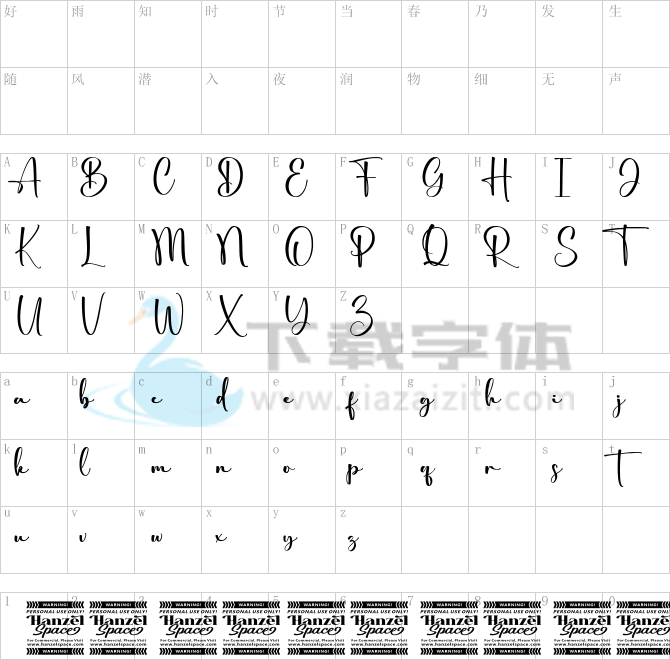
Airstone.otf字体下载,这款字体结构工整、笔画清晰,兼顾美观与易读性,适用于标题、正文、海报、包装、LOGO 等多种场景。字形优雅稳定,风格百搭耐看,适配日常排版与创意设计,让文字呈现更舒适、更具质感。Airstone.otf字体下载一笔一画,皆是细节,以均衡的比例、流畅的线条打造舒适视觉体验,字形端正大气,风格简约现代。无论是商业设计、品牌宣传还是日常排版,都能轻松驾驭,让文字更有格调与力量。Airstone.otf字体下载字体下载。